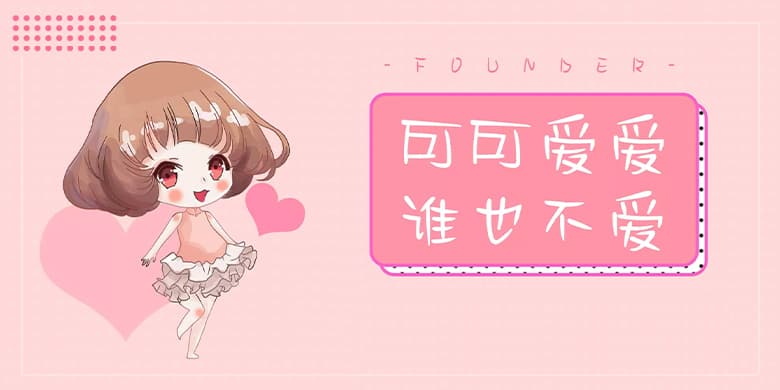
品牌:方正手迹设计师:俞亦婷发行时间:2019字库编码:大陆简体(GB2312-80)分类:创意书写字体属性:精品字
可可爱爱谁也不爱这款字体用笔干脆利落轻重交换,笔画多取斜势且带有一定的弧度,俏皮可爱而又放荡不羁,个性感十足极具特色。适用于少儿类的书刊、漫画、综艺影视字幕用字、商业类品牌广告和产品包装设计,以及社交网络的个性化用字。
品牌:方正手迹设计师:俞亦婷发行时间:2019字库编码:大陆简体(GB2312-80)分类:创意书写字体属性:精品字
可可爱爱谁也不爱这款字体用笔干脆利落轻重交换,笔画多取斜势且带有一定的弧度,俏皮可爱而又放荡不羁,个性感十足极具特色。适用于少儿类的书刊、漫画、综艺影视字幕用字、商业类品牌广告和产品包装设计,以及社交网络的个性化用字。